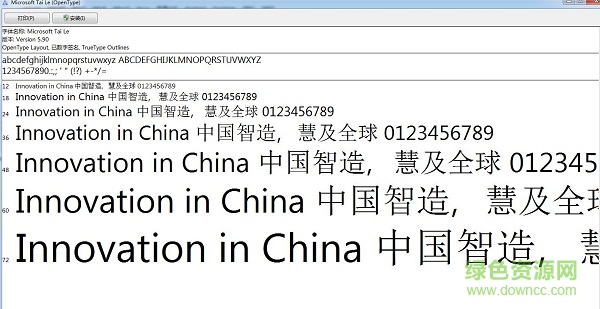
microsofttaile字體
microsoft tai le是什么字體?這是一款支持傣文輸入的無襯線字體,包括了microsoft tai le的常規(guī)體和粗體兩款,結(jié)體嚴(yán)謹(jǐn),平穩(wěn)干凈,易讀性強,有需要者歡迎免費下載!
microsofttaile字體